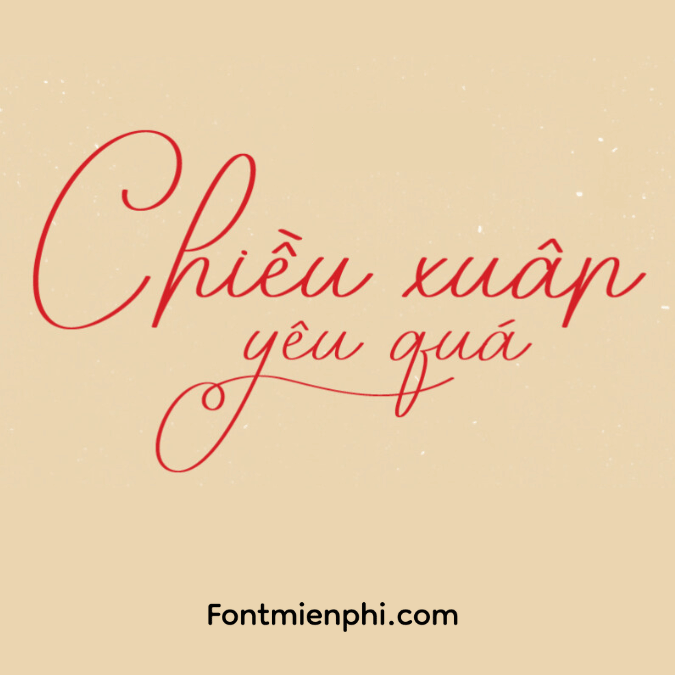
Giới thiệu bộ Font Việt hóa 1FTV VIP Daughter ,font tết
Chào đón không khí rộn ràng của mùa xuân, việc lựa chọn Font Miễn Phí phù hợp là yếu tố then chốt để tạo nên những ấn tượng thị giác mạnh mẽ. Trong số các lựa chọn hàng đầu, Font Việt hóa 1FTV VIP Daughter ,font tết nổi lên như một giải pháp hoàn hảo cho các nhà sáng tạo nội dung tại Việt Nam. Đây là bộ font mang phong cách hiện đại nhưng vẫn giữ được nét mềm mại, uyển chuyển, rất thích hợp để trang trí thiệp chúc mừng, banner quảng cáo hay các ấn phẩm truyền thông giáo dục nhân dịp đầu năm mới.
Đặc điểm nổi bật của font tết 1FTV VIP Daughter
Bộ font này được tối ưu hóa hoàn toàn cho bảng mã tiếng Việt, giúp người dùng tránh được các lỗi hiển thị dấu phổ biến. Với các nét chữ thanh thoát và cấu trúc cân đối, sản phẩm giúp truyền tải thông điệp ấm áp và tràn đầy hy vọng. Các bạn học sinh và giáo viên có thể dễ dàng sử dụng bộ font này để thiết kế báo tường hoặc tài liệu học tập sinh động hơn.
Cách ứng dụng Font Việt hóa 1FTV VIP Daughter ,font tết hiệu quả
Sáng tạo ấn phẩm học đường và gia đình
Để phát huy tối đa vẻ đẹp của Font Việt hóa 1FTV VIP Daughter ,font tết, bạn nên kết hợp với những tông màu truyền thống như đỏ, vàng hoặc xanh lá cây. Sự phối hợp này không chỉ làm nổi bật nội dung mà còn tạo cảm giác gần gũi, thân thuộc với văn hóa dân tộc. Việc sử dụng font chữ đúng cách sẽ giúp các tác phẩm thiết kế trở nên chuyên nghiệp và thu hút người xem hơn bao giờ hết.
Tổng kết về bộ font tết ấn tượng